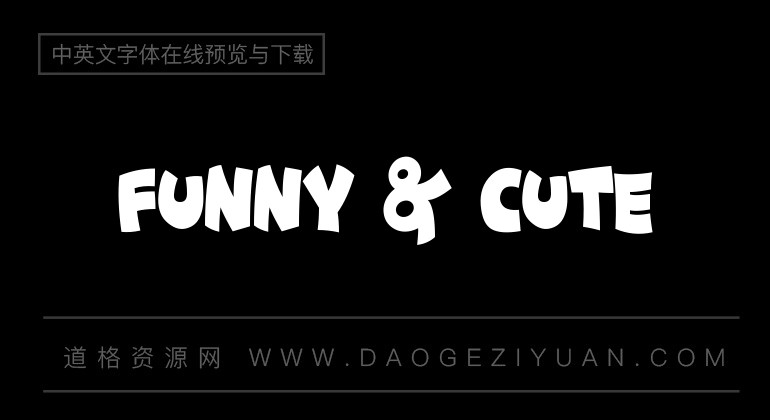
Funny & Cute
Funny & Cute 字体是一款简洁可爱的字体,它有着轻松可爱的设计风格,适用于各种不同的场景,比如商业广告、婚礼、礼品标签、儿童活动、文字装饰等等。它的字体主要是由椭圆形的字体组成,拥有柔和的线条和清晰的结构,能够给人一种可爱的感觉,同时又能够提高文字的可读性。
Funny & Cute是一款非常不错的手写艺术字体,具有很好的视觉感,适合于文化类的宣传设计、商业类品牌的广告和产品包装设计以及个性化文字排版等较多场景。